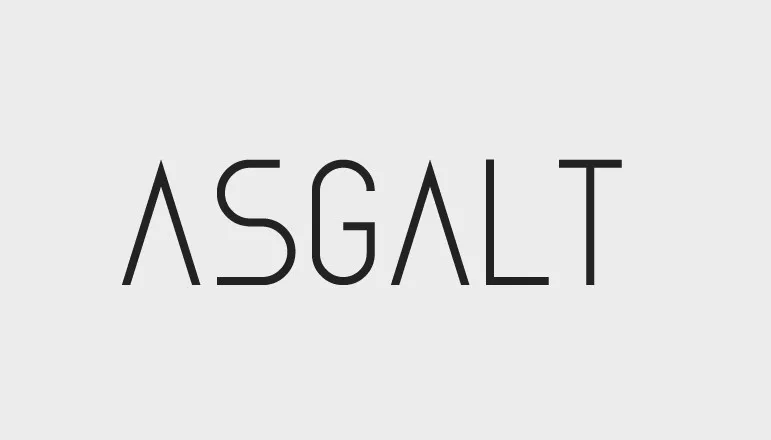
Asgalt Typeface – Fonte Grátis
Asgalt Typeface
Olá! Estou aqui uma oportunidade especial para você procurar por belas fontes com a belleza do BeFonts. Presentamo-nos Asgalt Typeface! Esteve criada pelo Hamilton e compartilhada pelo designer Remi Lagast, é um tipo de fonte limpa, que tem uma forma de cápsula geométrica. A forma cápsular fez dele mais conveniente para manusear ao longo do texto em longas seções, além de ser fina, tornando-o perfeito para logotipos, moda, papelaria, revistas, menus, livros, convites, cartões de agradecimento, embalagens, etiquetas, roupas e marketing. Isso abrange as necessidades tanto da marca quanto do design gráfico em uma variedade de aplicações. Asgalt Typeface certamente está se preparando para tornar-se sua fonte favorita.